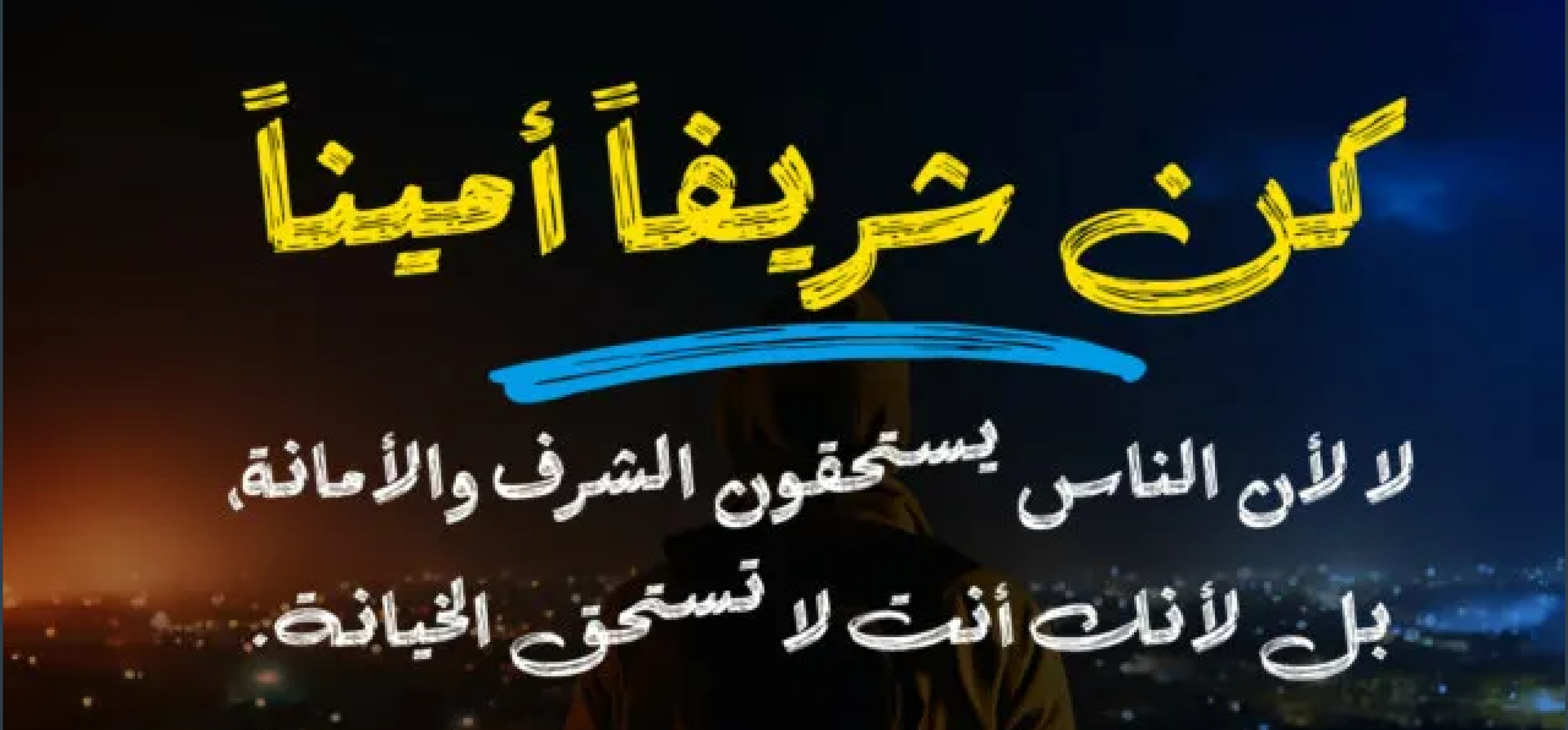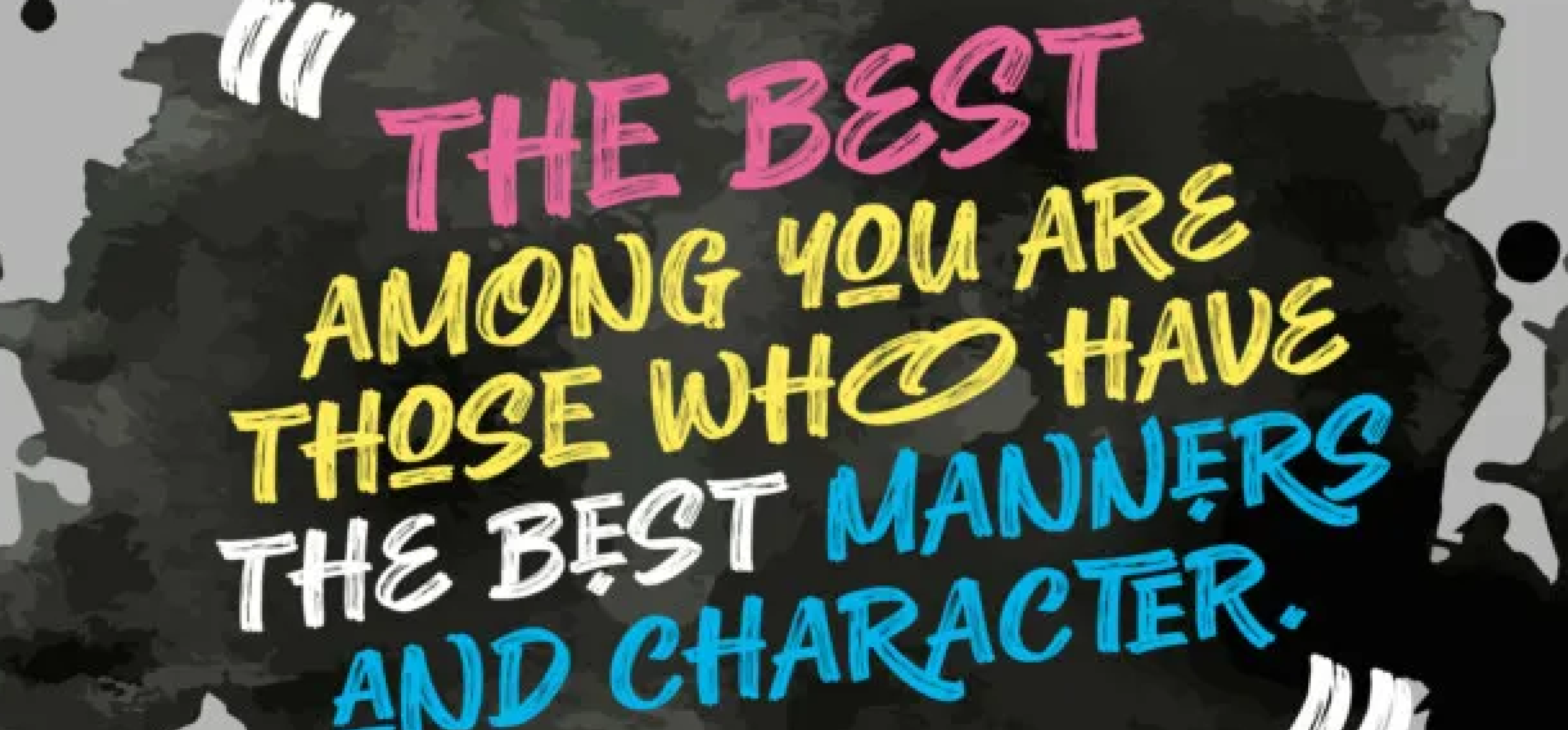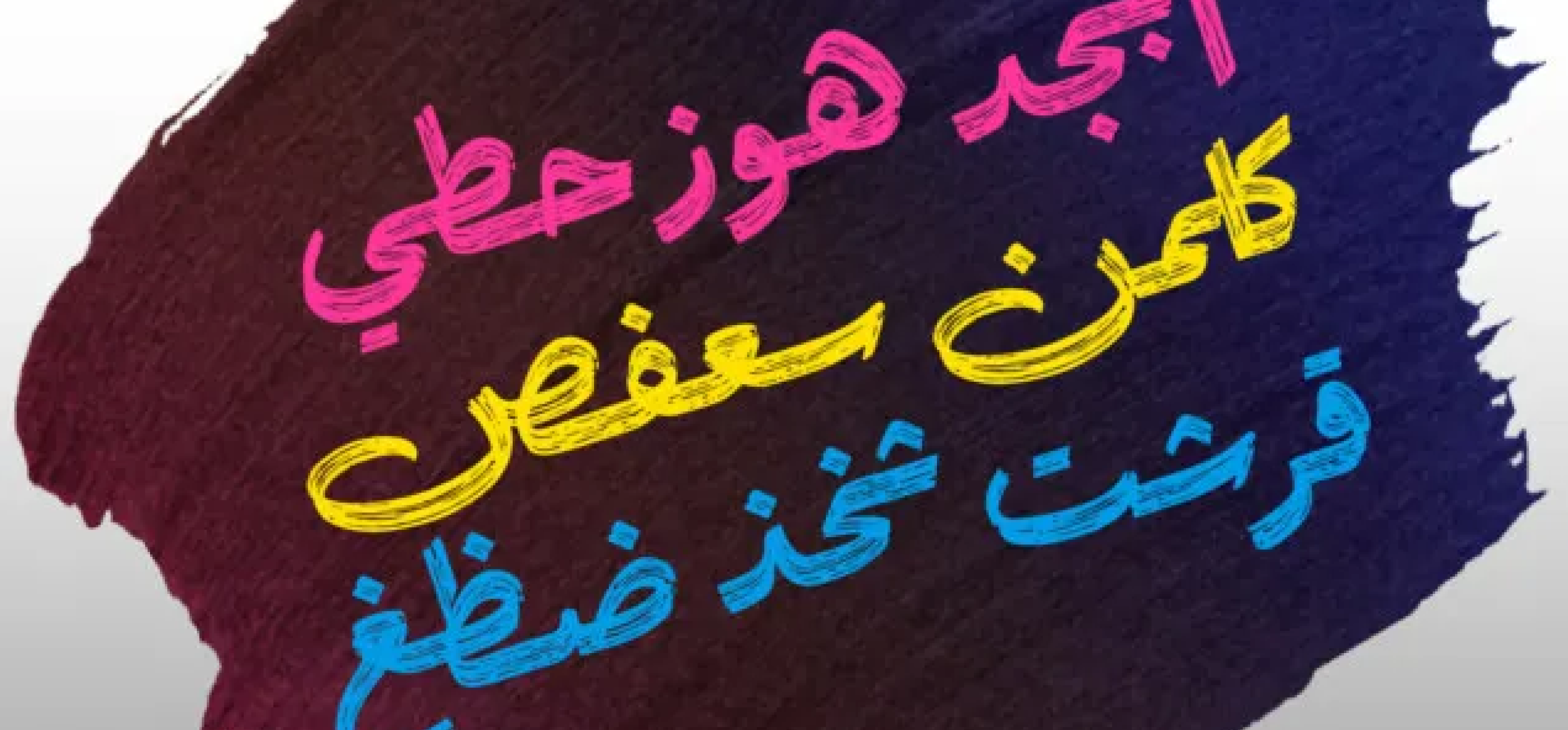
خط Lemon Brush Arabic هو خط يدوي مبهر يتميز بأسلوب ضربات الفرشاة الجافة الديناميكية. يتميز الخط بملمسه الفريد وسلاسته، مما يجعله خيارًا مثاليًا لإضفاء لمسة فنية وشخصية على مختلف المهام التصميمية. يتضمن الخط العديد من البدائل والربطات (Ligatures)، مما يعزز مظهره اليدوي الطبيعي ويجعل كل استخدام له يبدو جديدًا وعفويًا. يُصنّف ضمن خطوط العرض (Display Fonts).